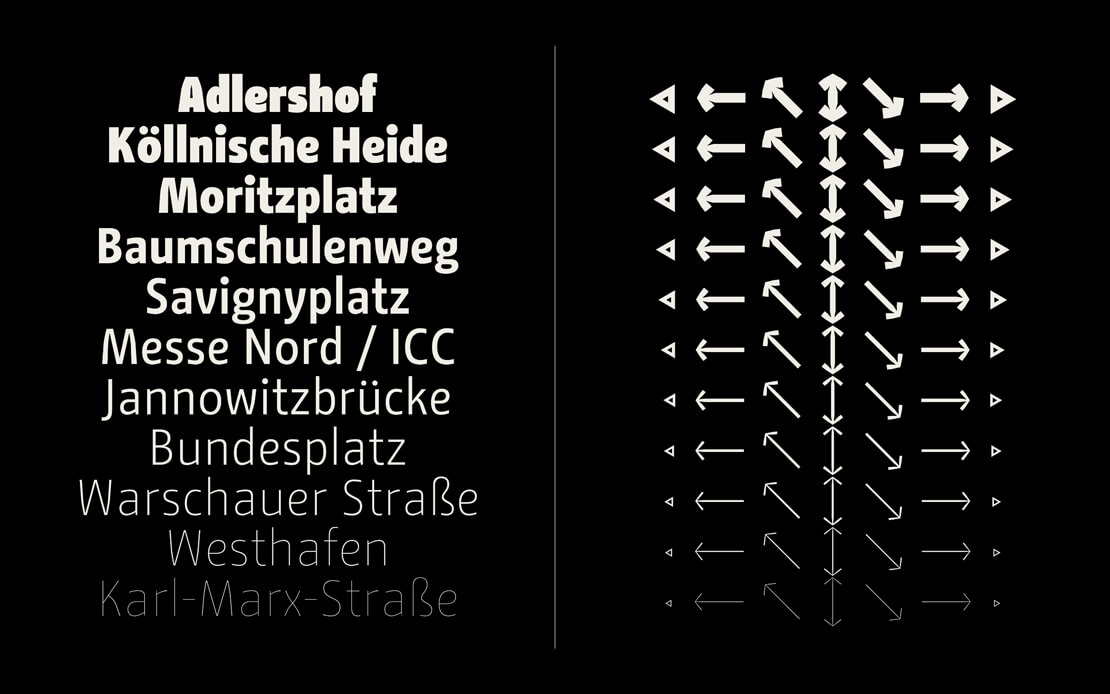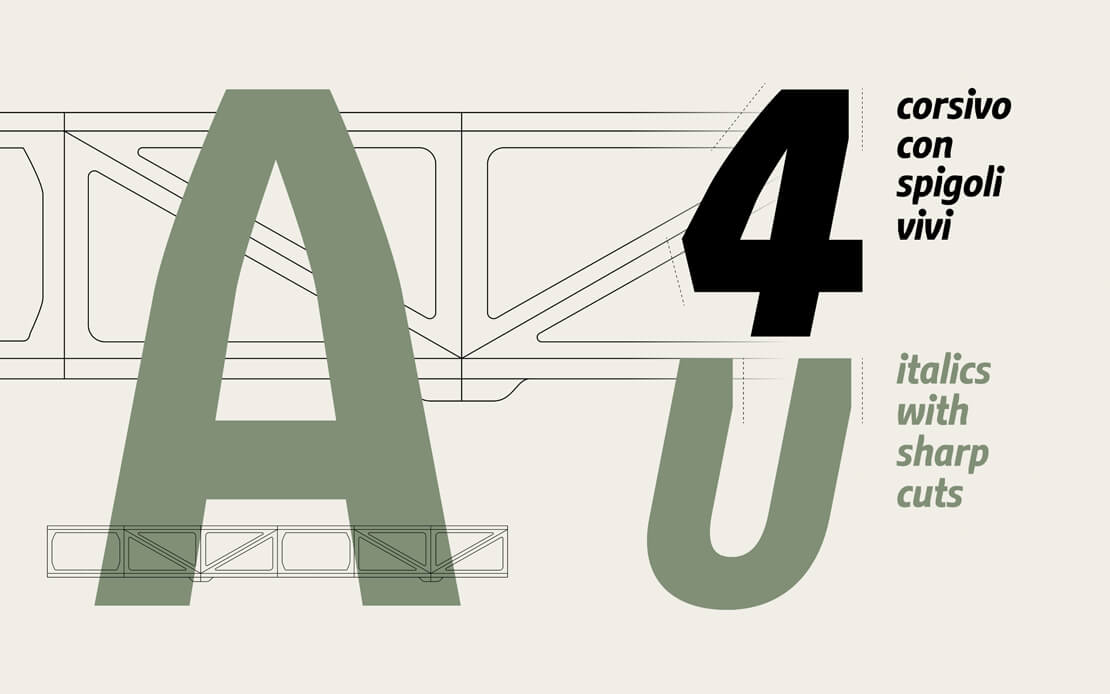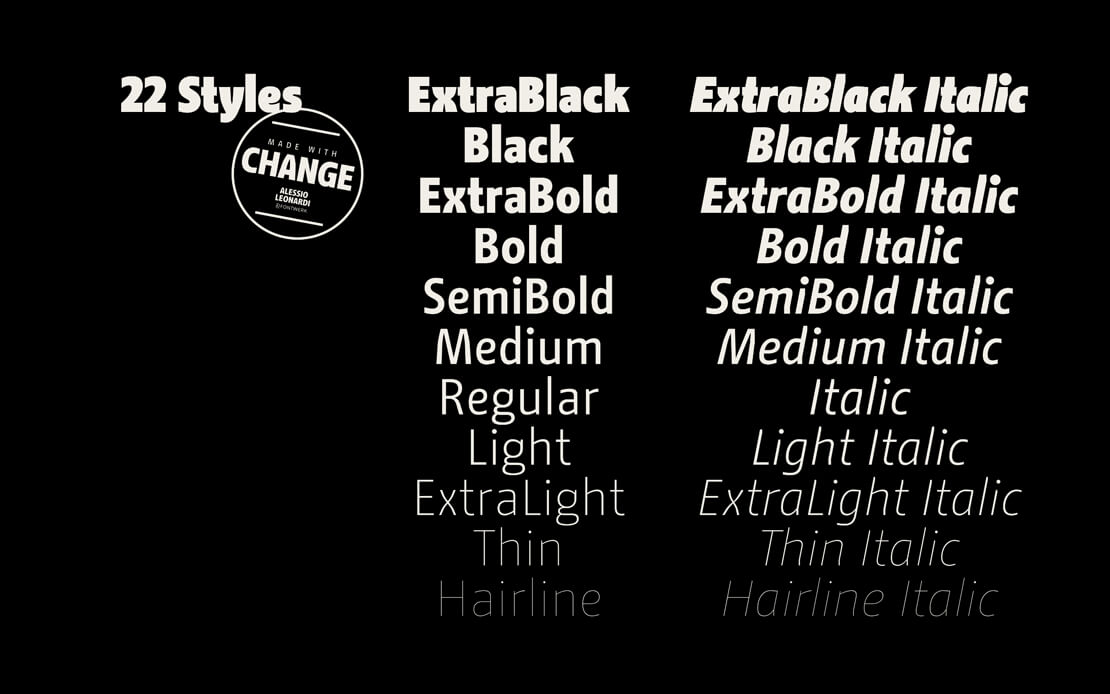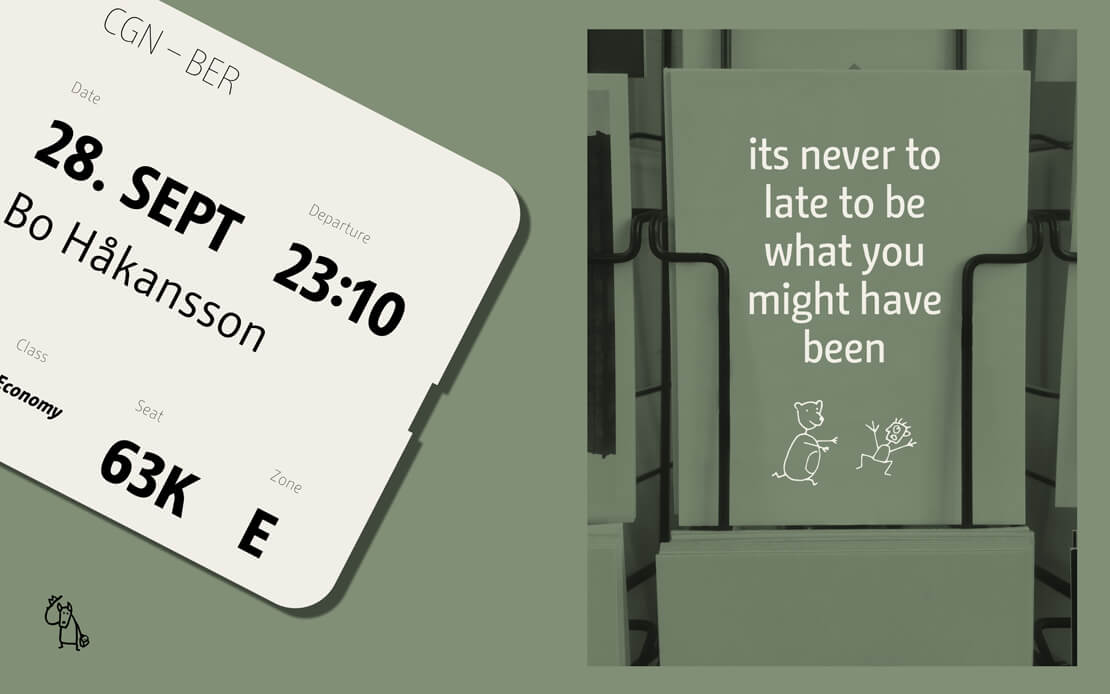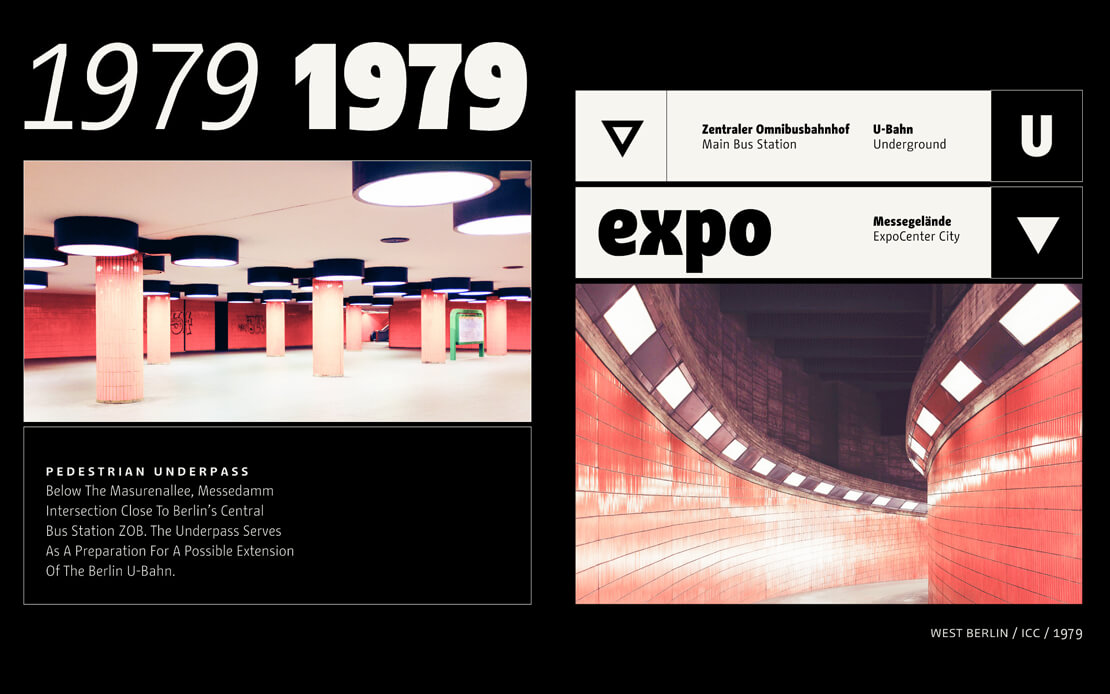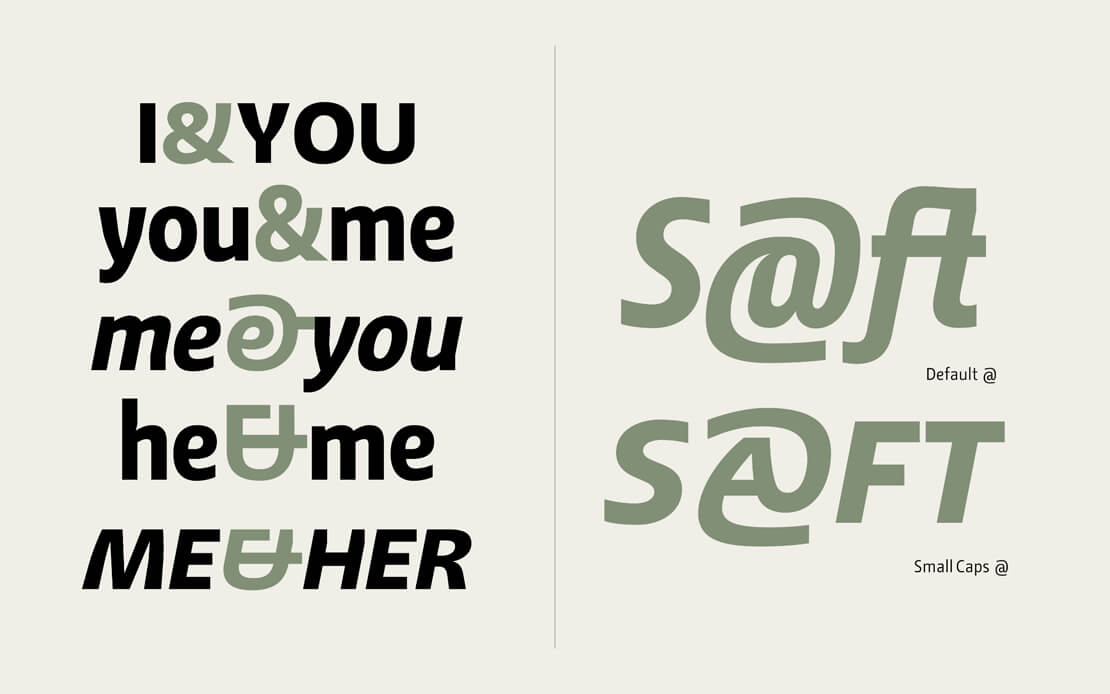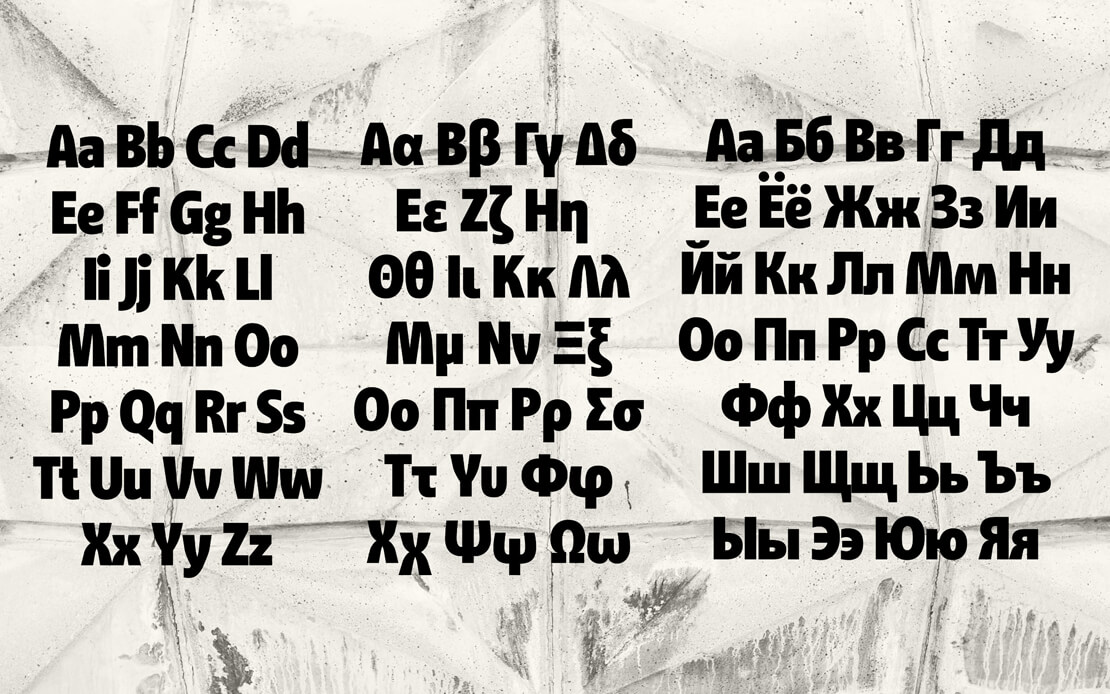
Schriftfamilie »Change« bei Fontwerk erschienen
Die ehemalige Hausschrift der Hauptstadt und weiterhin aktuelle der Berliner Feuerwehr darf nun zeigen, was in ihr steckt. In Kooperation mit Alessio Leonardi hat Fontwerk die »Change« komplett überarbeitet. Die Schriftfamilie liegt jetzt in 22 Schnitten und in zwei Variable Fonts vor.
Ursprünglich entworfen für Berlin
Am 11. März 2008 stellte der Regierende Bürgermeister von Berlin die neue Stadtmarketing-Kampagne »Be Berlin« vor, mit der die vielfältigen Facetten der Hauptstadt bekanntgemacht werden sollten.
Als treibende Kraft fungierten seinerzeit Dreizeiler, die in der eigens entworfenen Schrift Change gesetzt wurden. Nach 12 Jahren im »öffentlichen Dienst« hat Fontwerk in Kooperation mit Alessio Leonardi die Schrift jetzt optimiert und erweitert, damit sie bei Marken und kreativen Projekten ebenfalls zur Entfaltung kommen kann.
Optimiert für Flexibilität
Der Fokus der Anpassungen und Ergänzungen lag zunächst auf der Change-(Sans-)Familie, deren Strichstärken von fünf auf elf erweitert wurde. »Hairline«, »Thin«, »ExtraLight«, »Regular«, »Medium«, »SemiBold«, »ExtraBold«, »Black« und »ExtraBlack sind aufeinander abgestimmt und sollen für eine größere Flexibilität sorgen.
Um den Weißraum der Punzen und um die Buchstaben präziser zu kontrollieren, wurde die gesamte Familie auf der Basis von drei Mastern mit modernen Tools und unter Berücksichtigung gestiegener Ansprüche neu aufgebaut. Mit dem erstmals zur Verfügung stehenden Variable Fonts lassen sich zusätzliche Strichstärken zwischen den Extremen »Hairline« und »ExtraBlack« einstellen.
Außerdem wurde der Zeichenvorrat der Change im Rahmen ihrer Optimierung vergrößert. Das betrifft beispielsweise auch die Glyphen für die nicht-lateinischen Sprachen, die von Amélie Bonet (Kyrillisch und Griechisch) und Donny Truong (Vietnamesisch) geprüft und getestet wurden. Schließlich erweitern Kapitälchen in allen Schnitten die typografische Vielfalt.